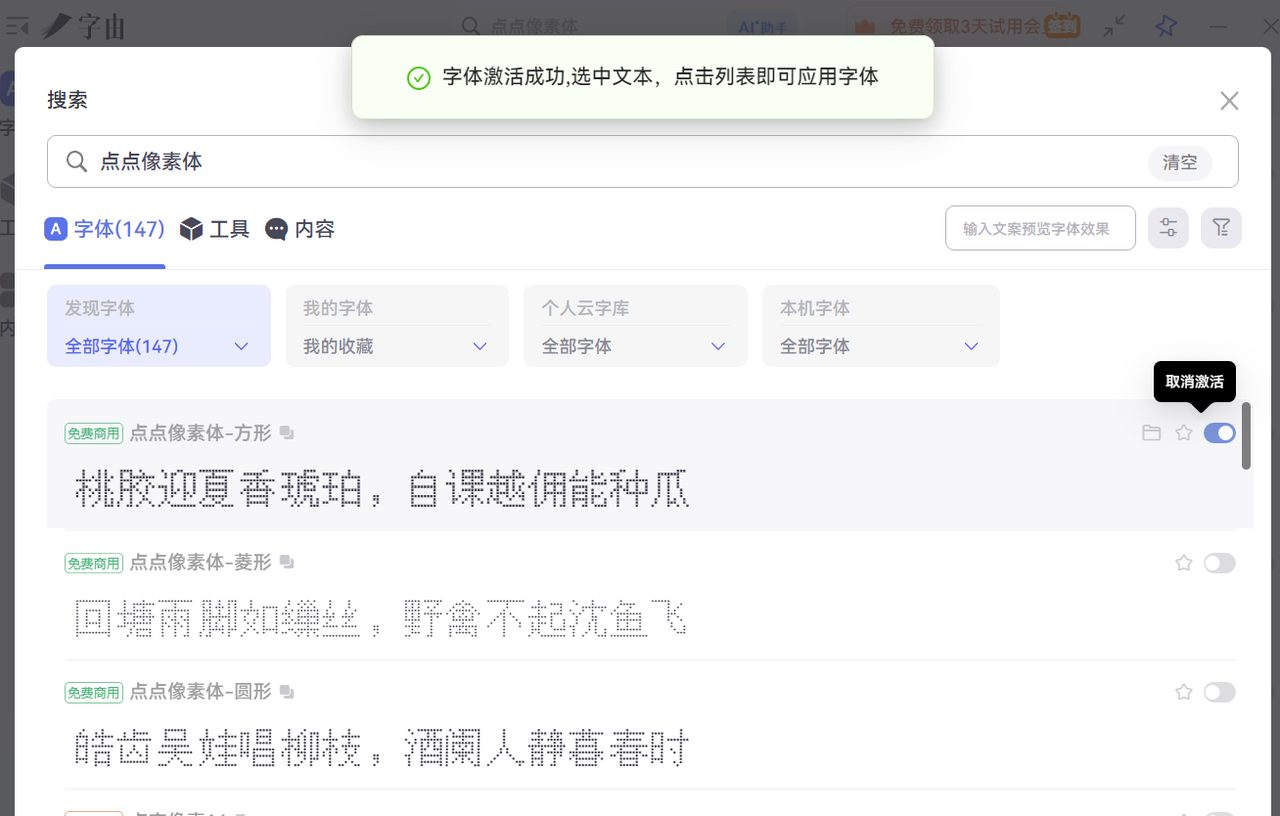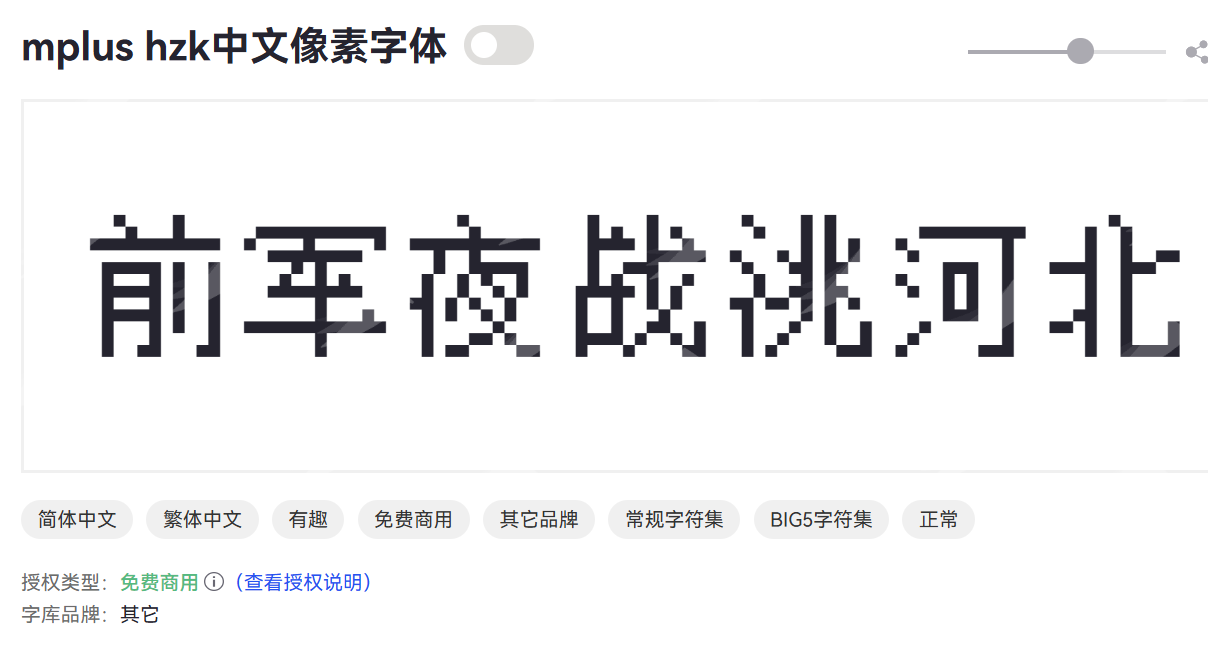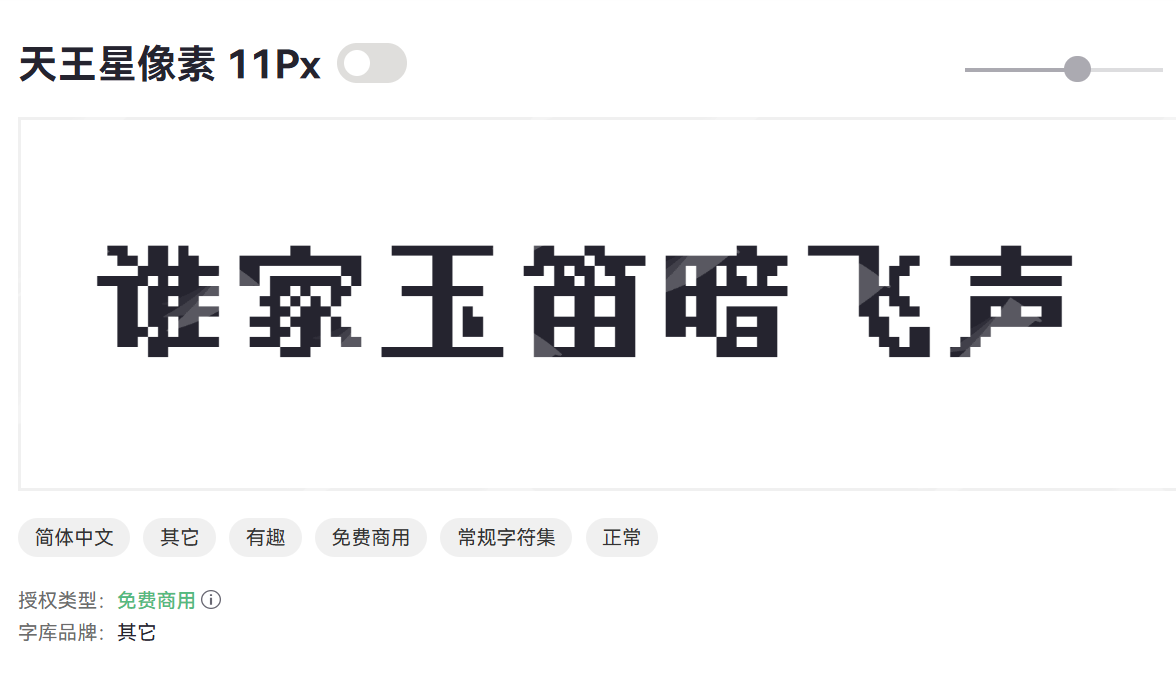
像素字体可以商用吗?6款可以免费商用的像素字体分享
一提到“像素”,大家脑海里可能立刻会浮现出早期的电脑游戏、电子表格,甚至是老式电视屏幕的画面。没错,它不像我们现在看到的平滑、精美的印刷体,而是由一个个独立的“像素点”组成的,充满了独特的复古韵味和数字美学。很多小伙伴想使用像素字体,但不知道是否可以商用,本文就给大家介绍6款可以免费商用的像素字体。
6款可以免费商用的像素字体
缝合怪像素字体
缝合怪像素字体是一款免费开源、可商用的泛中日韩黑体无衬线像素字体,由多款像素字体 “缝合” 而成,主打复古游戏与编程界面风格。
独特、复古的视觉效果,能唤起玩家对早期电子游戏的怀旧感。适合独立游戏 UI、对话、菜单、像素画文字、代码编辑器、终端、命令行界面等使用场景。
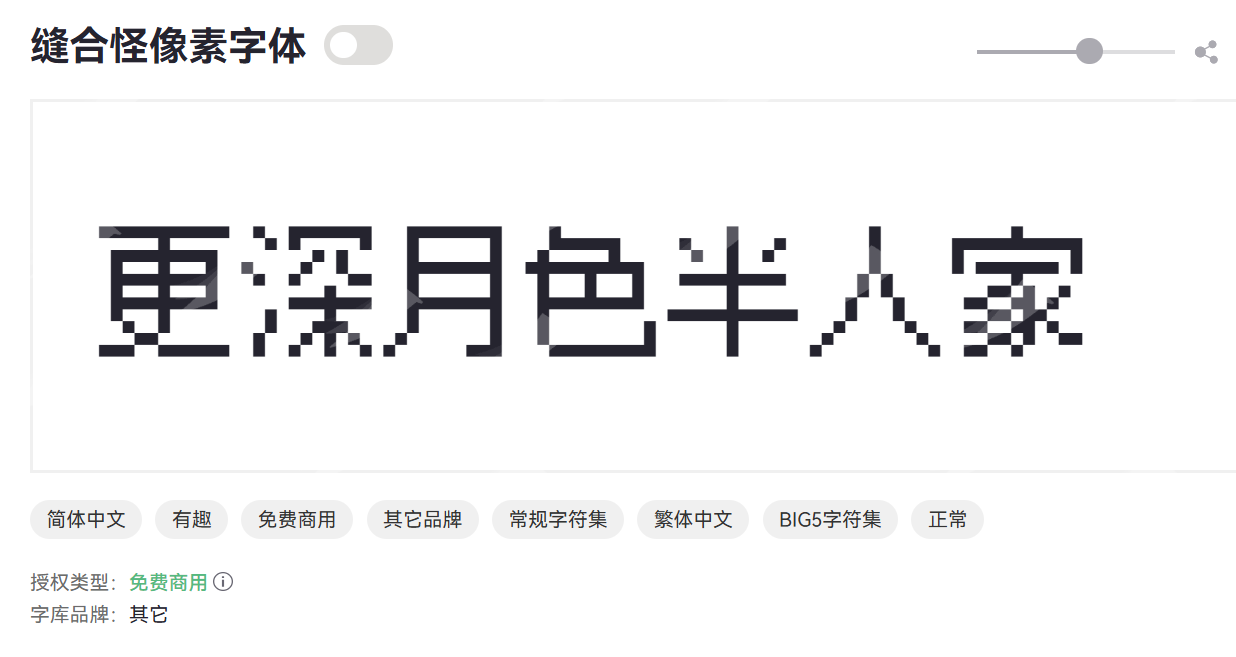
mplus hzk中文像素字体
mplus hzk中文像素字体是一款专为中文设计的像素字体。它遵循了像素字体的基本规则,即用有限的像素点来构成每一个汉字,旨在在低分辨率环境下提供清晰可读的中文显示。
mplus hzk中文像素字体清晰的像素网格结构,每个笔画由离散的像素块组成。字形设计简洁、方正,易于识别.在低分辨率屏幕上显示效果出色,不易模糊。
天王星像素
天王星像素是一款基于文泉驿点阵库改造、主打不粘连粗体的中文像素字体,免费可商用,适合复古界面与像素游戏。适合场景:需要个性化和独特视觉效果的游戏开发、创意插画、海报设计、具有未来感或科幻色彩的设计。
点点像素体
点点像素体是一种由“点”构成的像素字体。它可能在笔画的连接和处理上更加强调“点”的集合感,使得字体在像素化的基础上,又带有一些别致的纹理或质感。
点点像素体由细小的像素点组成,具有颗粒感。整体风格可能显得轻盈、细腻,或者具有一种独特的“抖动”感。适合具有艺术感或实验性的像素艺术场景。
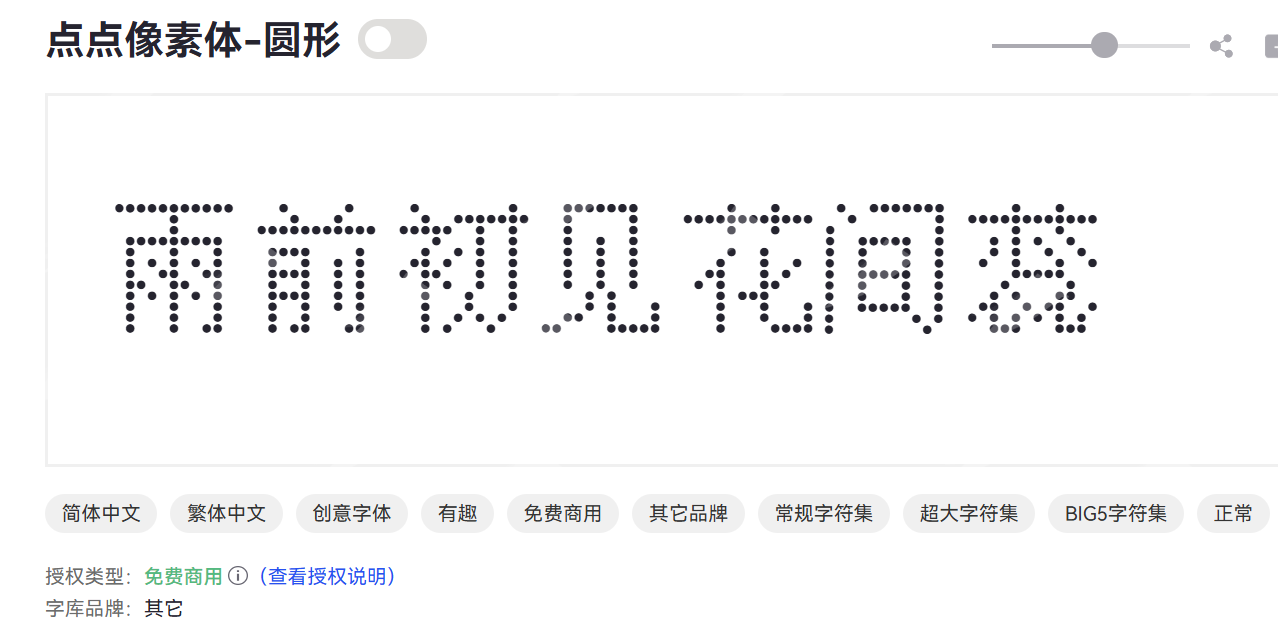
莫妮卡像素圆体
莫妮卡像素圆体适合儿童游戏、绘本、休闲类手机游戏、卡通形象、表情包设计等场景。
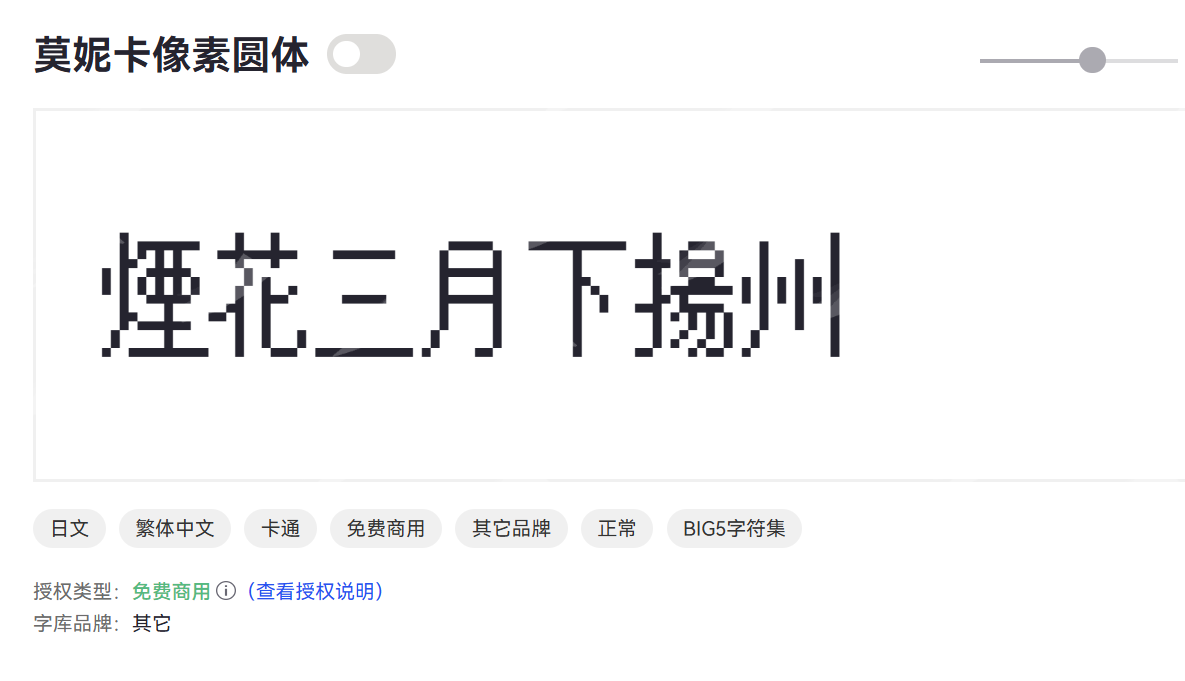
破晓像素
破晓像素是 2025 年 10 月发布的12px 等宽像素字体,由 diaowinner 基于 Fairfax、ZLabs Bitmap、Galmuri 整合构建,采用 SIL Open Font License 1.1(OFL) 授权,个人 / 企业可免费商用、修改、分发,无需署名。
破晓像素整合三款经典像素字体,保留原字形并优化编码冲突(如 PUA 移至 U+10E000 起),Powerline 符号归位,兼顾中西日韩与终端符号场景。